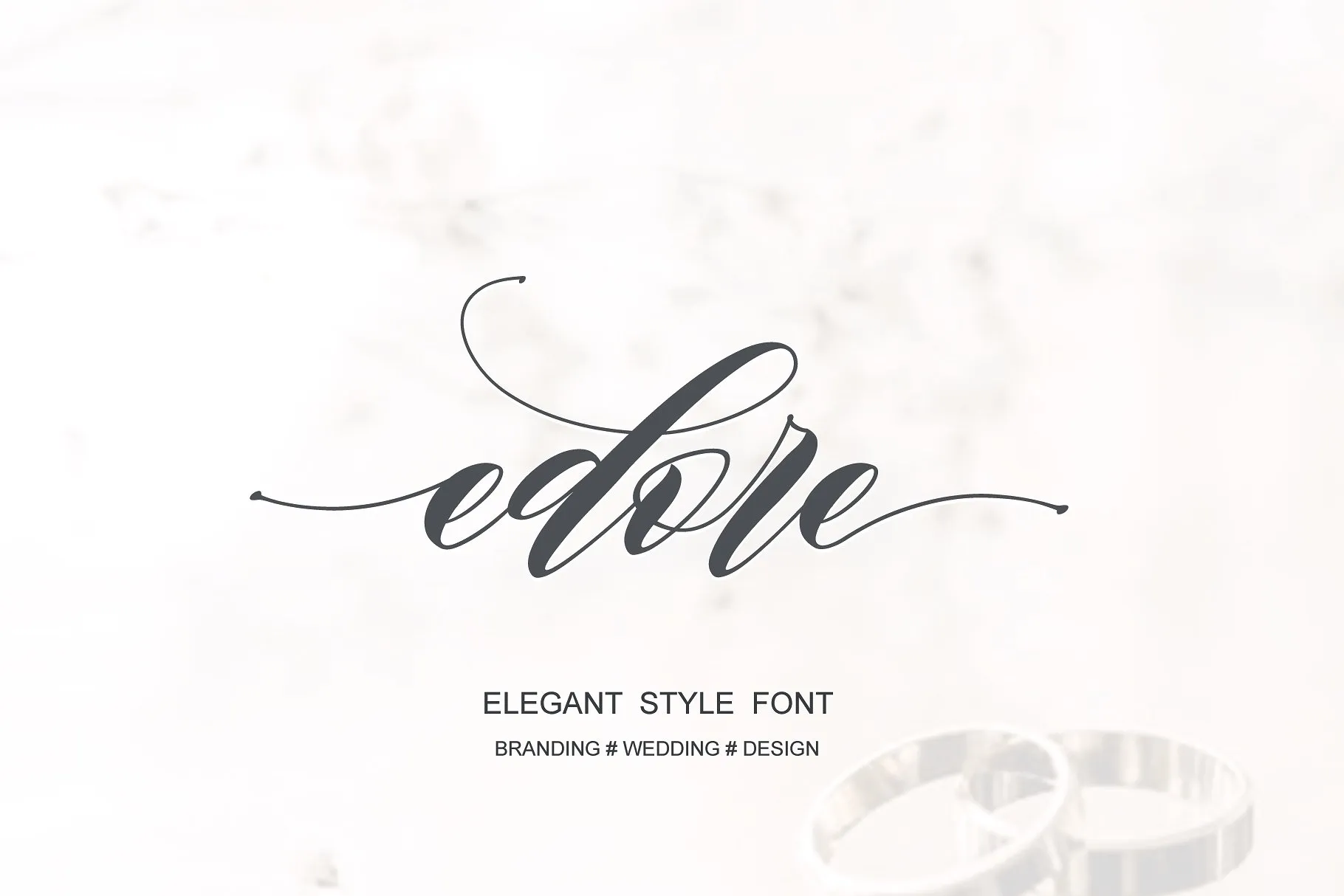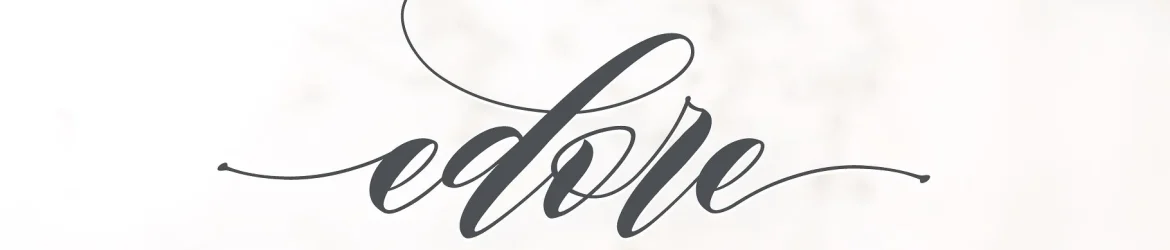
Edore Script Font é uma fonte script que transforma a tipografia em arte vibrante e bela. Ideal para trabalhos que valorizam estilos orgânicos e naturais, Edore destaca-se como um estilo elegante de caligrafia moderna. Esta fonte permite que você junte diversos estilos de fontes conforme desejar, adicione até mesmo as finas variações ornamentais ou banners, e transforme até mesmo uma única palavra em algo fascinante. Seja para logotipos, logos, identidades corporativas, casamentos, moda, rótulos, capa de livros, camisetas, posts do Instagram ou qualquer outro tipo de projeto, Edore traz um ar elegante e sofisticado ao seu trabalho. Convidamos você a explorar as possibilidades criativas que essa fonte oferece para tornar seus projetos ainda mais profissionais e imponentes.